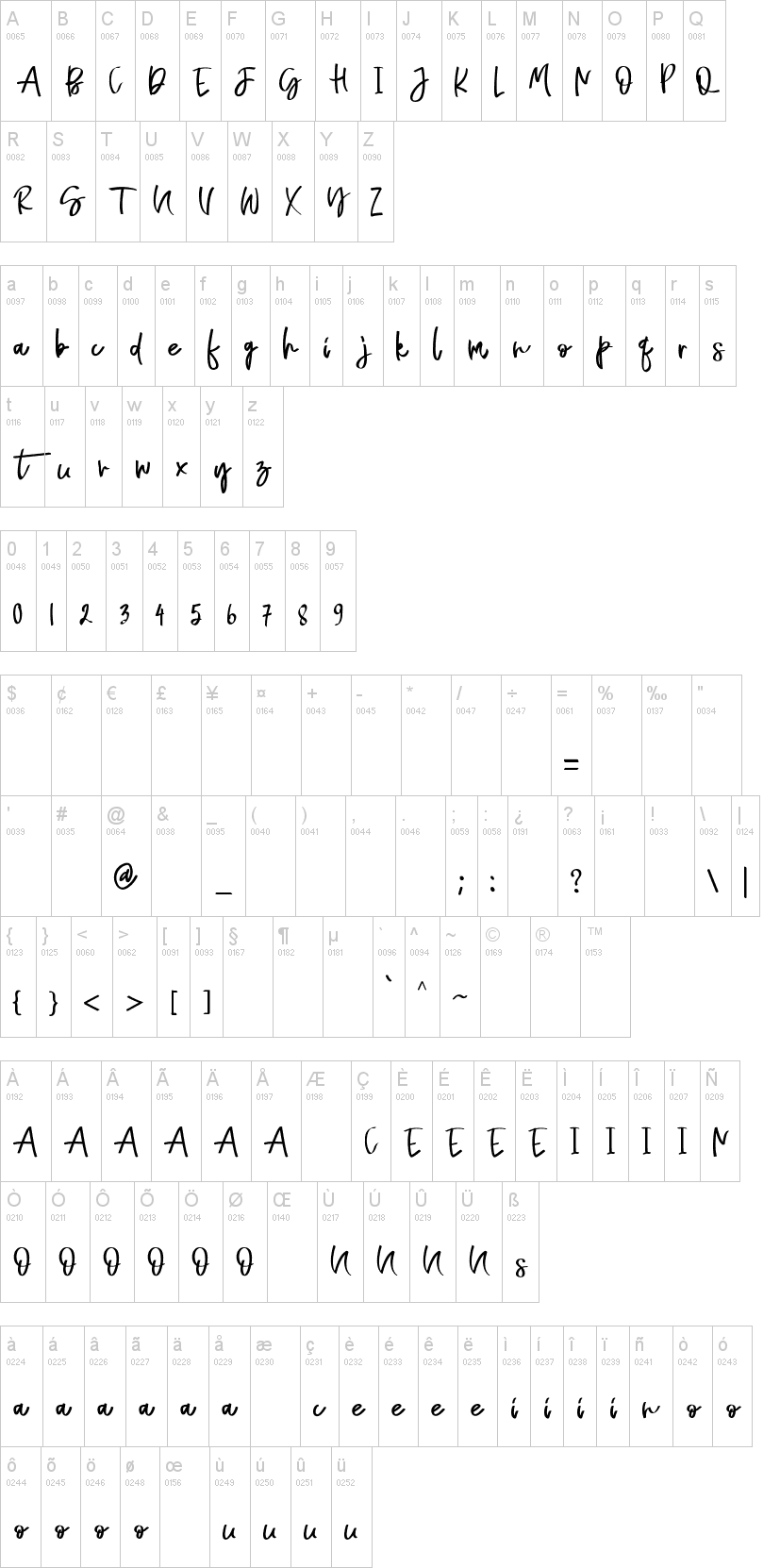
Naycila 字体是一种极具特色的西班牙语字体,它的设计灵感来自于西班牙传统的艺术和文化。Naycila 字体的特点是,它的字体设计极具西班牙特色,富有传统西班牙风格,让文字显得优雅而又有趣。Naycila 字体是一款精致而优雅的字体,适用于各种文字类型,可以用于制作海报、活动宣传资料、网站标题等,能够给人以温暖的感觉,让文字更加优雅而有趣。内容介绍
Naycila是一款非常不错的手写艺术字体,具有很好的视觉感,适合于文化类的宣传设计、商业类品牌的广告和产品包装设计以及个性化文字排版等较多场景。